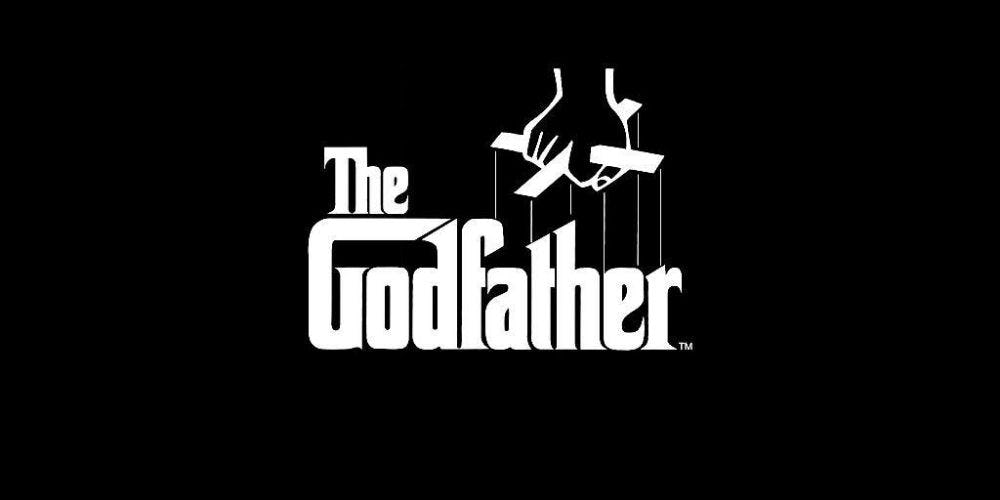
¡Es momento de darle a las tipografías de películas el reconocimiento que merecen!
Si bien los films destacan más por los actores, el argumento y la cinematografía, la tipografía de una película es un elemento artístico tan bien elaborado que se perdurará en la mente del espectador por un largo tiempo.
Las tipografías de películas se pueden apreciar en los banners, posters, merchandising y hasta en los créditos al inicio de una función de cine. Sin embargo, ¿no sería genial tener a nuestra disposición estos tipos de letras de cine para uso personal?
¡Afortunadamente estás en el lugar indicado! En la siguiente nota podrás encontrar una lista de las mejores tipografías de películas que querrás instalar inmediatamente en tu ordenador.
¿Qué tan importantes son las tipografías de películas?
Rosa Rodríguez, docente del curso online de Diseña con Tipografía: Técnicas y aplicación, señala que la tipografía es la representación gráfica del texto hablado y que nace con la idea de que se pueda prefabricar los textos, para que luego sean reproducidos en masa. En el caso de la tipografía en el cine, esta forma parte de la línea gráfica del film y quedará plasmada en cualquier pieza promocional.
¿Cómo saber si una película ha dejado huella en la audiencia? ¡Sencillo! Tienes que ver si logra identificar los diferentes elementos del film, como la música, los diálogos o los escenarios. En el caso de las fuentes de películas, aunque creas que pueden pasar desapercibido, muchas de ellas han pasado a ser icónicas.
Por ejemplo, ¿recuerdas la tipografía de Harry Potter? La memorable P con forma de rayo agrega un detalle muy especial al título del film y cada vez que veas esta fuente se te vendrá a la mente los mejores momentos de la saga del joven mago. ¡Lo mismo sucede con las tipografías de Disney!
Por eso, toda buena película tiene una tipografía que lo caracteriza. Nada es al azar en el mundo del cine y detrás de la producción hay diseñadores encargados de lograr hacer las tipografías de películas. ¿Tú, recuerdas alguna?
1. Disney
Si hablamos de Disney, todos pensamos en películas animadas clásicas y actuales. Es tan poderosa esta casa de producción que la mayoría de sus películas son un éxito comercial. Por esta razón, la productora audiovisual conserva una tipografía de película que lo caracteriza.
Los trazos con curva, gruesos y ese aspecto infantil es el sello de esta tipografía de película que Disney usó desde sus inicios y se mantiene en la actualidad.
Las tipografías de películas son tan importantes para Disney que, incluso hasta ahora, en los créditos iniciales de cualquiera de sus films, los elementos que no pueden faltar son: Mickey Mouse, el castillo de Disney y el logo de la marca con esta tipografía mundialmente reconocida.
Waltograph Disney es una de las mejores tipografías de películas que necesitas descargar. Ahora sí, le darás ese toque mágico a tus diseños.
2. Jurassic Park
En esta lista de tipografías de películas, no podemos dejar de mencionar al tipo de letra de Jurassic Park. Un film de dinosaurios necesita una tipografía que nos lleve muchos años atrás y el equipo creativo detrás de este film logró hacerlo.
Regresando a los dinosaurios, piedras, antigüedad y polvo es lo que transmite la tipografía de la película Jurassic Park. El film de Steven Spielberg es considerado un clásico y su producción y tipo de letra son inolvidables.
Si eres un fan de esta producción cinematográfica, de seguro que reconoces esas letras con trazos toscos y rectos que hacen referencia a las piedras antiguas. Esta tipografía para logos de películas es inconfundible.
Si quieres utilizar esta tipografía de película en tus diseños puedes descargar Jurassic Park y empezar a crear un mundo de dinosaurios y fósiles en tu edición.
3. Star Wars
Todo fanático de la Guerra de las Galaxias reconoce el sonido del film y la tipografía de la película. La fuente que utilizó Star Wars relaciona al lector con el espacio y el futuro, lo necesario y justo para una película de ciencia ficción.
En toda la saga, la producción conservó la tipografía de la película porque reconocen lo importante que es para la identificación de su público y es por eso que, hoy en día, Star Wars es una fuente de inspiración para muchas cosas. Es más, nos atrevemos a decir que esta fuente está entre las tipografías de películas más famosas.
Así que, si tienes que hacerle un diseño o una sorpresa a un fanático usando la tipografía de Star Wars, hacer su nombre con la fuente Star Jedi es un buen inicio para sorprénderl@.
4. Transformers
Una producción de máquinas enormes que se transforman y que pelean entre ellas. Esto es Transformers y tiene una tipografía de película especial. Un poco futurista, moderna y fuerte.
La tipografía cinematográfica de Transformers se puso en tendencia cuando se estrenó la producción y surgieron muchos seguidores de la película. ¿Vehículos que se transportan en robots para proteger el universo? ¡Es una idea alucinante!